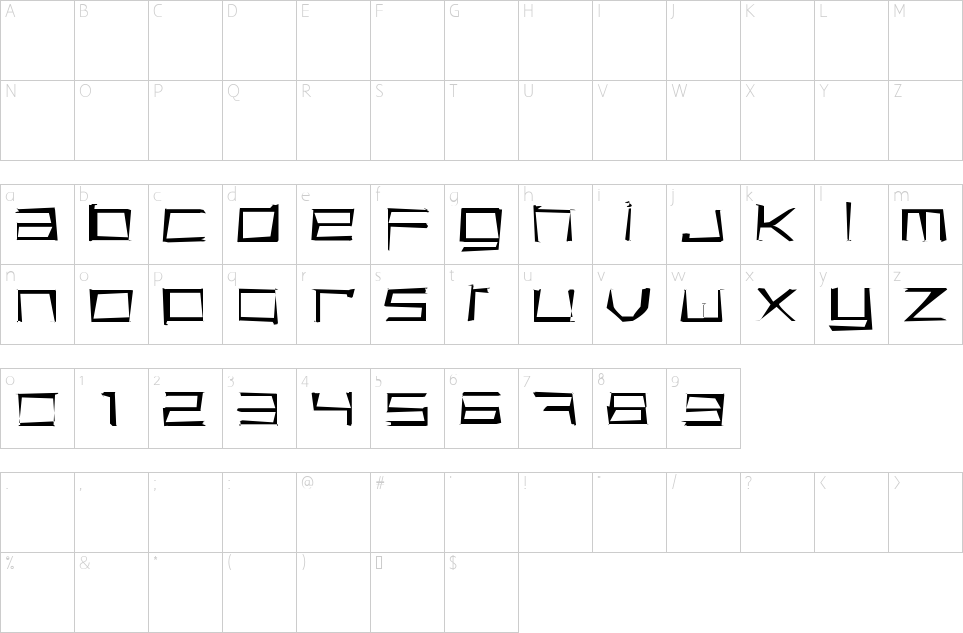
A fonte Basica Cartoon oferece um toque divertido e único para seu próximo projeto gráfico. Desenhada por Qbotype, esta font é perfeita para uma paleta de estilos que vai de cartões de aniversário até ilustrações para crianças. Com suas linhas leves e design claramente inspirado em cartoons, Basica Cartoon traz uma dose de diversão sem comprometer a funcionalidade. Seja para usar no seu site pessoal ou para uma campanha publicitária, essa font é uma escolha atraente para aqueles que procuram um toque único e divertido. Descarregada por quase cinco mil vezes, essa font livre de pagamento é uma opção elegante para designers gráficos e criativos de todos os níveis.